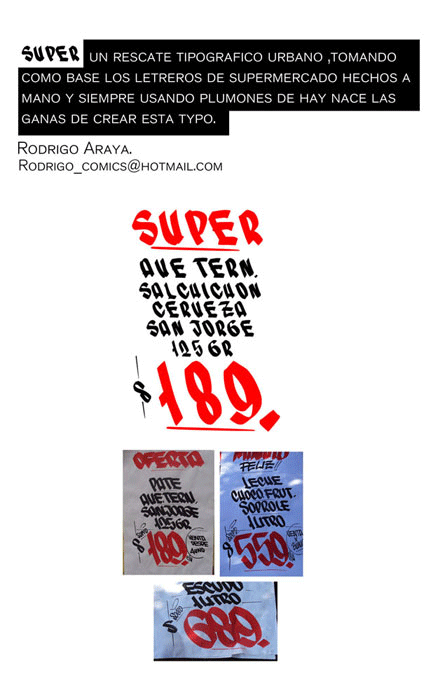
"SUPER" UNA FUENTE INSPIRADA EN LETREROS DE SUPERMERCADOS CHILENOS, LOS CUALES TIENE UNA FORMA MUY EN PARTICULAR DE ESCRIBIR CON PLUMONES CON UN NUEVE REDONDIADO , ESO QUISE TOMAR. ----------------------------------- RODRIGO ARAYA SALAS RODRIGO_COMICS@HOTMAIL.COM |